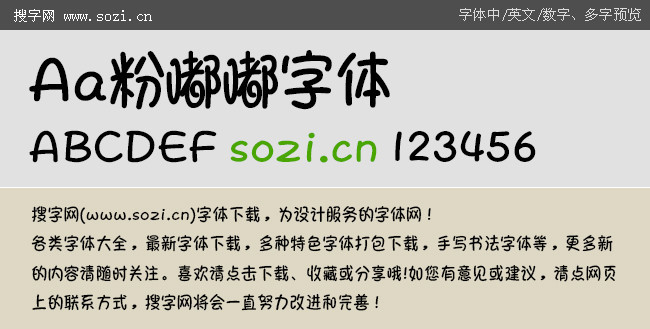
Aa粉嘟嘟字體
搜字網(wǎng)給大家提供一款A(yù)a粉嘟嘟字體中文卡通字體下載,這是一款手寫(xiě)風(fēng)格的卡通字體,充滿童趣,非常可愛(ài),適合手機(jī)顯示使用、卡通畫(huà)冊(cè)、兒童用品宣傳廣告等應(yīng)用(此字體為個(gè)人非商用版,如需商用請(qǐng)聯(lián)系作者購(gòu)買版權(quán))。